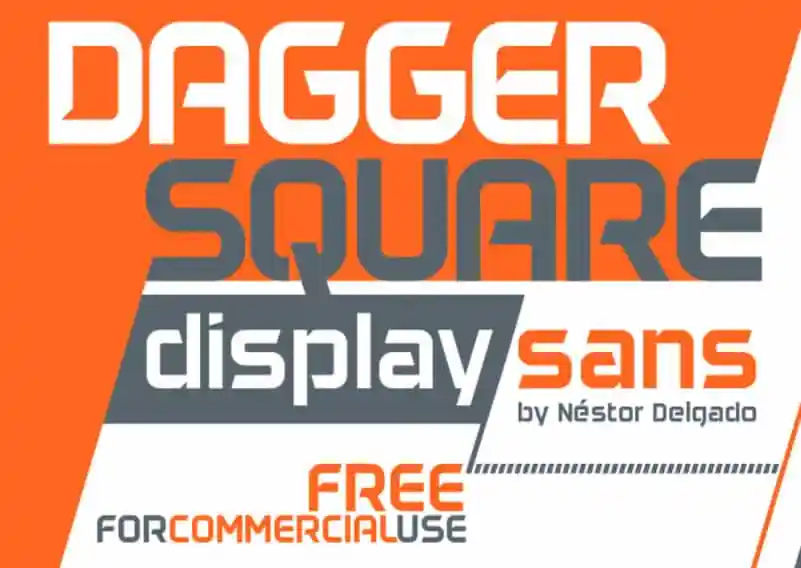
Daggersquare Display Font – Fonte Grátis
Daggersquare Display Font
A Daggersquare Display Font é uma família geometricamente estilizada de sans serif que combina ângulos aguçados com ligaturas interativas. Esta tipografia é perfeita para os profissionais de design, especialmente aqueles atentos aos detalhes e à personalização de seus projetos. Com sua abordagem clara, o designer Hamilton criou uma fonte ideal para se adaptar a um vasto espectro de aplicações, como desenho esportivo, logomarcas, cartazes, embalagens, folders, camisetas e muito mais. Esta fonte apresenta uma variedade de estilos distintos, garantindo que tenha sempre o elemento certo para seus projetos em constante evolução. Com Daggersquare Display Font, seu design nunca ficará sem vida.